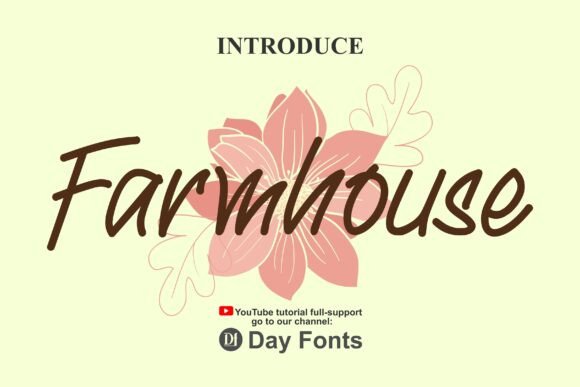
Farmhouse
Farmhouse: A Fonte Bouncy que Transforma Seus Projetos Artesanais
Se você está em busca de uma tipografia que una elegância e diversão, a fonte Farmhouse chegou para ser a estrela dos seus trabalhos criativos. Com um design sofisticado e ao mesmo tempo descontraído, ela se destaca em projetos de craft personalizados, trazendo aquele toque especial que faz toda a diferença.
- Design bouncy e elegante: As curvas suaves dão sensação de movimento, enquanto os detalhes finos mantêm a sofisticação.
- Versatilidade incrível: Ideal para convites, cartões, etiquetas, estampas de camisetas e até para branding de pequenas marcas.
- Personalização completa: Permite ajustes de cor, espaçamento e peso, garantindo que cada peça tenha a sua identidade única.
- Impacto visual: A combinação de estilo “fancy” com um toque doce cria uma atmosfera acolhedora, perfeita para eventos como casamentos, festas temáticas e lançamentos de produtos artesanais.
Em resumo, Farmhouse não é apenas mais uma fonte; é uma ferramenta de branding que eleva o nível dos seus projetos, entregando resultados profissionais e cativantes. Se você quer que seus trabalhos artesanais se destaquem nas redes sociais e conquistem o coração do público, esta fonte bouncy é a escolha certa.